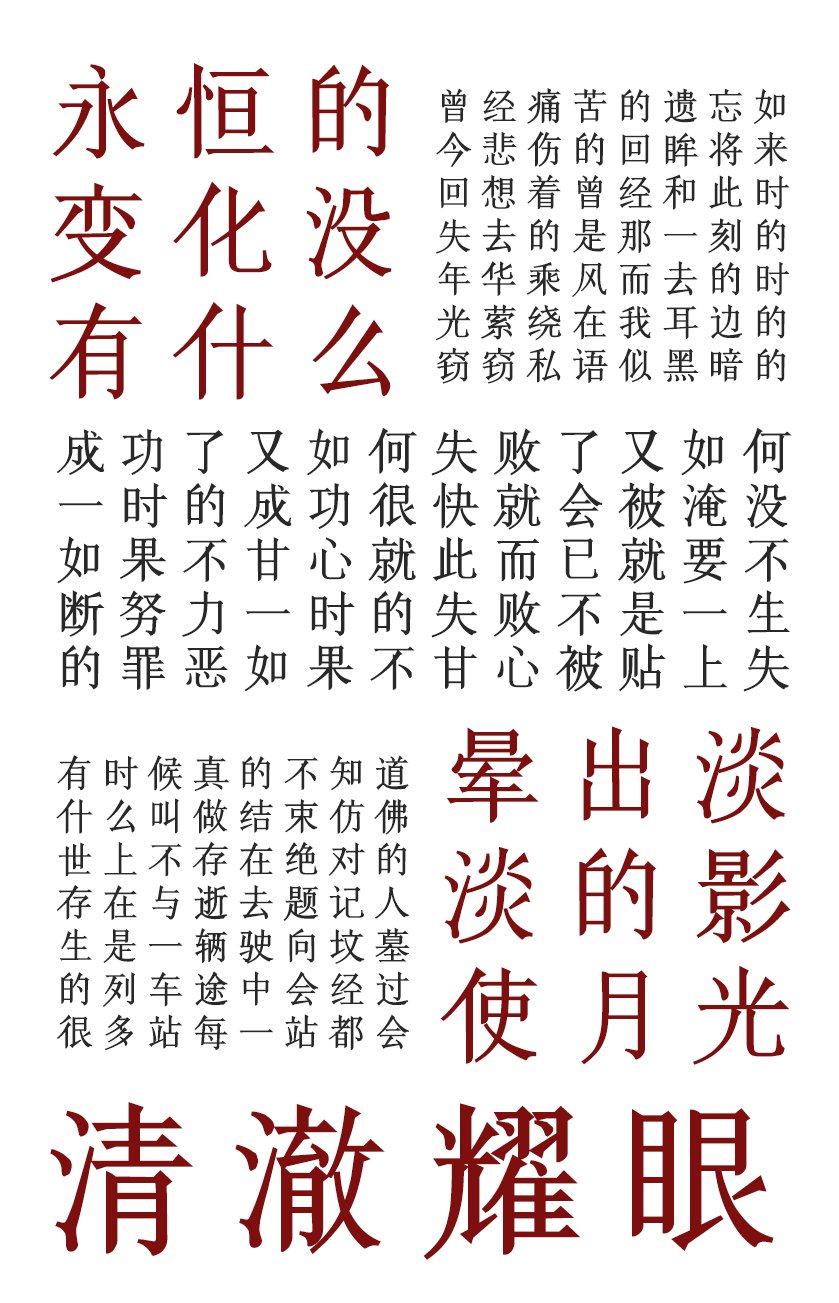
最常用的字体就是“宋体”,宋体字规范,笔画有粗有细,端庄秀丽,常见于政府文件、商业类文档或者一些比较艺术的海报,它可以作为标题使用,也可以作为正文,是我们办公中使用最频繁的字体。这里给大家推荐一款印品字库的字体-印品清版宋。
清版宋字体创作灵感源于清代康熙年间出版的《康熙字典》,结合清朝时期风格的宋体特点所创制的一款新宋体。字型修长、撇捺舒展、体态优雅,适合办公使用与屏显阅读。
字体字样展示: